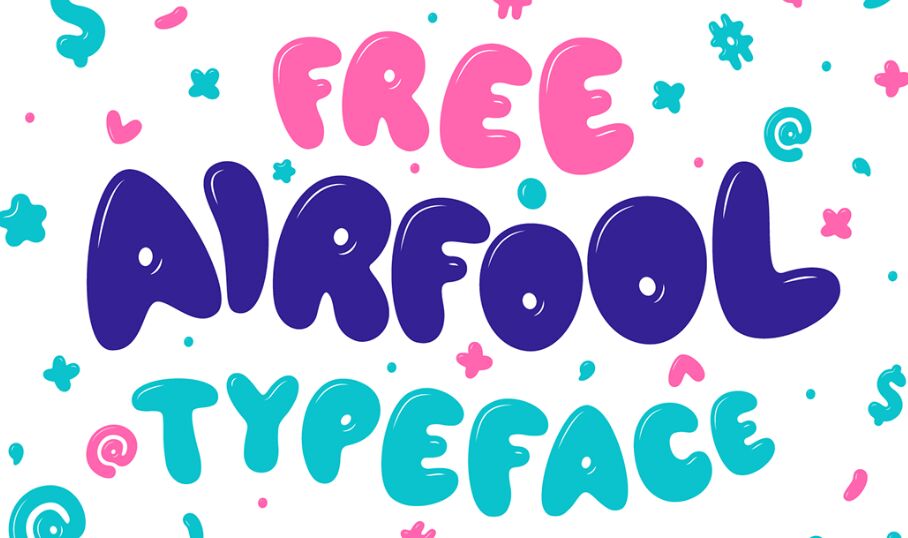
20+ Best Free Kid Fonts For Children's Books And Design Projects (2024 Update)
20+ freie Fonts für Kinderbücher und Designprojekte
Wenn Sie ein Projekt für Kinder gestalten, sollten Sie die 10+ besten handgemachten, verspielten, entzückenden Kinder-Schriftarten nicht verpassen, die kostenlos für Ihre nächsten kindbezogenen Projekte wie Websites, Bücher, Flyer, Einladungskarten und vieles mehr sind.
Kinderinteressen Schriftart
Kinderinteressen Schriftart ist eine eigenwillige fette Schriftart mit einzigartiger Buchstabenform. Eine Schriftart mit fröhlichem und verspieltem Aussehen. Diese Schriftart wurde speziell für die Anwendung in Logos und anderen verschiedenen formalen Formen wie Einladungen, Etiketten, Logos, Zeitschriften, Büchern, Gruß-/Hochzeitskarten, Verpackungen, Mode, Make-up, Schreibwaren, Romanen, Etiketten oder jedem anderen Werbezweck perfekt gemacht.
Kinderbücher Kostenlose Schriftarten
Kinderbücher ist eine fette, verspielte, handgeschriebene serifenlose Schriftart. Es bringt uns allen Freude und Glück. Inspiriert von Handlettering mit Markerstift mit fettem und kräftigem Stil.
Hallo Spark Niedliche Schriftart
Von Grußkarten über Poster bis hin zu Kleidung – die Vielseitigkeit und Freundlichkeit von Hello Spark machen es zu einer Display- und Textschriftart der Wahl. Seine verspielten, aber lesbaren Buchstabenformen eignen sich wunderbar für Designs sowohl für Erwachsene als auch für Kinder. Laden Sie Hello Spark herunter, um Ihrem nächsten Designprojekt eine gesunde Dosis Freude zu verleihen.
Bulito Schriftart
Eine niedliche und verspielte Schriftart kostenlos für den persönlichen Gebrauch.
Balpaq Kostenlose Comic-Schriftart
ROCKEY Schriftart
Retro Cartoon Schriftart
TOYZ KOSTENLOSE SCHRIFTART
BRICK KOSTENLOSE SCHRIFTART
Eine verspielte und freche Schriftart mit endlosen Möglichkeiten.
YeeMaff Kostenlose Schriftart
Retro Vibes Schriftart
Die Lima KOSTENLOSE SCHRIFTART
Eine verspielte Schriftart kostenlos für den persönlichen und kommerziellen Gebrauch.
Swipy Kostenlose Schriftart
Eine handgezeichnete Cartoon-Schriftart.
No Virus Kostenlose Schriftart
Hoola Kostenlose Schriftart
Spielvolle Schriftart
CORGI kostenlose Schriftart
Eine lustige handgeschriebene Großbuchstabenschrift. Perfekt für Branding, Poster, Logos, Titel und mehr.
Oggi Schriftart kostenlos
PRINTIPO Schriftart kostenlos
AIRFOOL Kostenlose Schriftart (Kostenlos für kommerzielle Nutzung)
SNOT Schriftart
Arco (Kostenlos für kommerzielle Nutzung)
Eine lustige Typografie, mit abgerundeten Kanten, mit mehr als 80 Zeichen, seine Alphabete in Großbuchstaben. Diese Schriftart ist kostenlos für den persönlichen und kommerziellen Gebrauch.
Crafto Kostenlose Schriftart (Kostenlos für kommerzielle Nutzung)
qtpi Schriftart
Krypto-Tierschriftart
Tierschriftart nützlich für Kinder und Bildung.